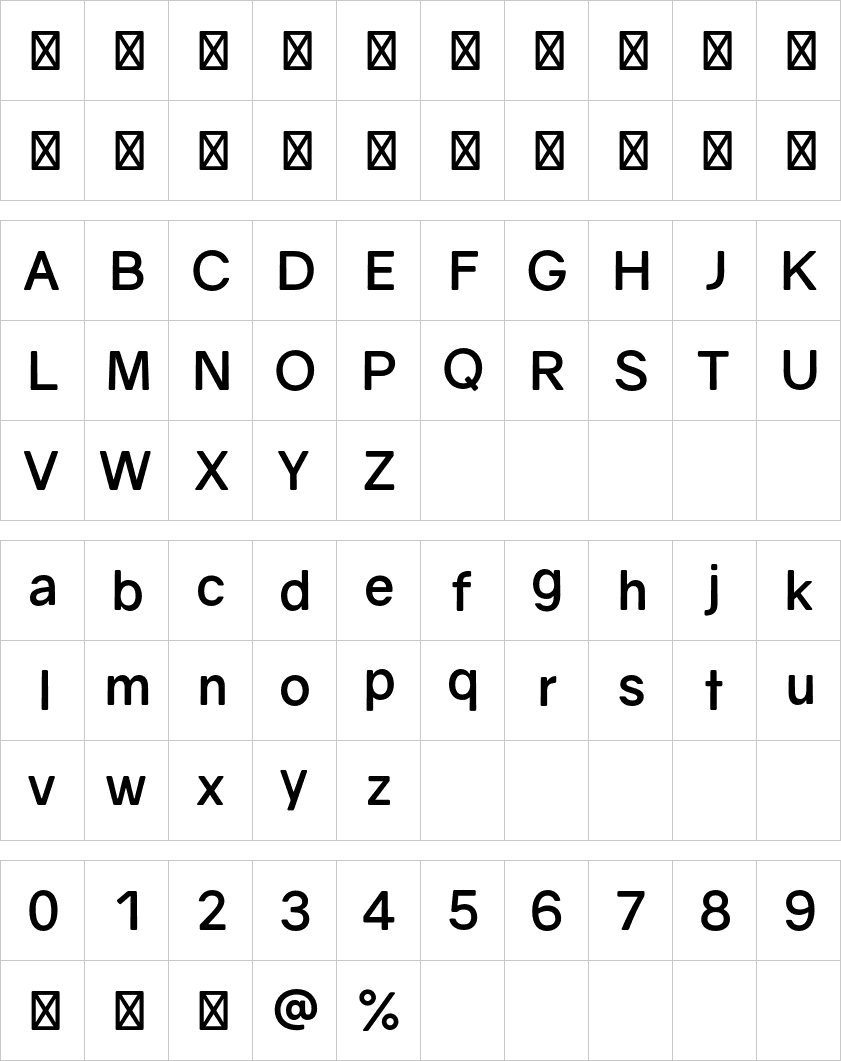
Gravity Font
Gravity 是一个排版实验,源于加深我对这门学科知识的渴望。Gravity 也是一种新的几何无衬线字体,设计有平衡和大计数器。该字体使用“重力”作为字体的独特、功能和美学特征。它将被“Accademia di Belle Arti Palermo”用作官方字体。Gravity 也是我的第一个字体。希望你喜欢!如果您想尝试,请免费下载。